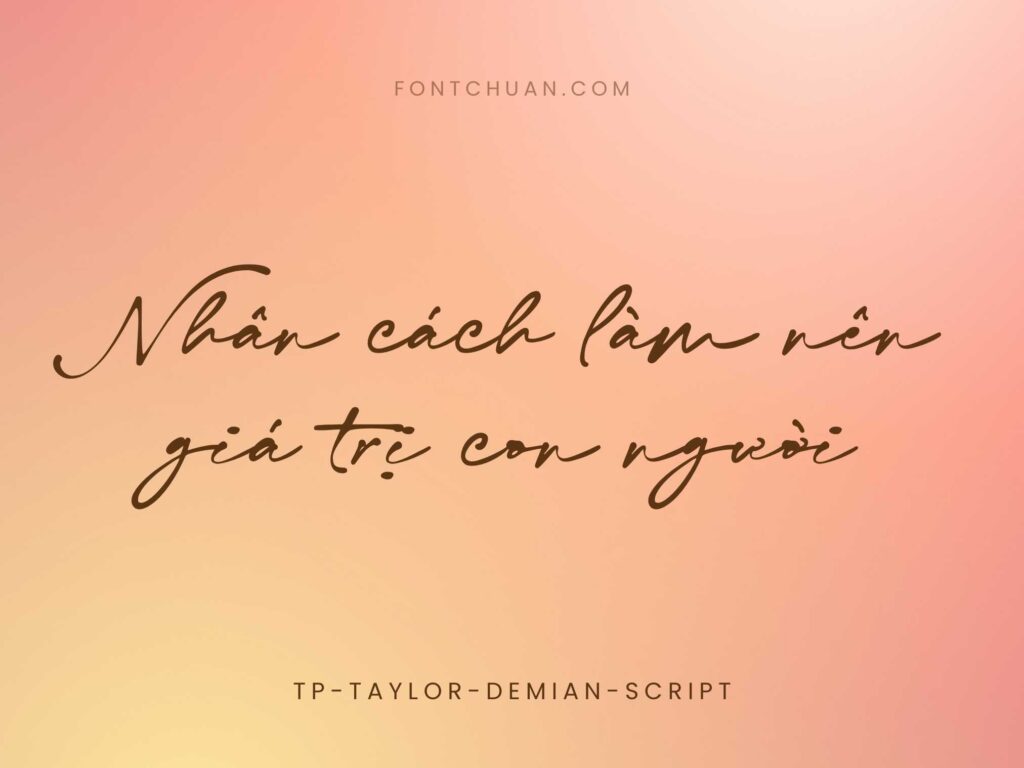
Font TP Taylor Demian Script Việt Hóa
Taylor Demian là một Font chữ ký thanh lịch, được thiết kế bởi Get Studio. Font này thể hiện phong cách chữ ký tự nhiên, mang lại cảm giác tinh tế và mượt mà cho các dự án thiết kế. Với các nét chữ uyển chuyển và mềm mại, Taylor Demian phù hợp cho các ứng dụng như thiết kế logo, thiệp mời, tiêu đề và các dự án sáng tạo khác. Không chỉ dừng lại ở đó, khi kết hợp cùng các Font cổ trang, Taylor Demian có thể tạo nên sự giao thoa độc đáo giữa nét hiện đại và cổ điển, mang lại chiều sâu nghệ thuật cho thiết kế. Font đã được Việt hóa để hỗ trợ tiếng Việt bởi Tuỳn Pucca, giúp người dùng Việt Nam dễ dàng sử dụng trong các dự án thiết kế. Font này được sưu tầm và chia sẻ bởi thành viên của Font Chuẩn, đáp ứng nhu cầu sử dụng đa dạng trong cộng đồng thiết kế.
Đặc điểm thiết kế của Taylor Demian bao gồm các nét chữ mềm mại và tự nhiên, tạo cảm giác thân thiện và gần gũi. Font này phù hợp cho các ứng dụng như thiết kế logo, thiệp mời, tiêu đề và các dự án sáng tạo khác. Các ngành nghề phù hợp bao gồm quảng cáo, nghệ thuật và thiết kế đồ họa.